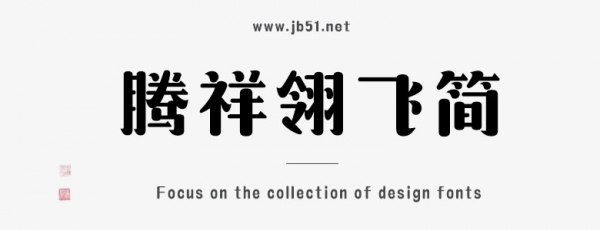
騰祥翎飛簡(jiǎn)是一款不錯(cuò)的藝術(shù)字體,由騰祥字庫出品,既保持字形規(guī)范、布白合理,保證版面效果整齊,又不失字形本身的俏麗與意趣,風(fēng)格獨(dú)特、別致,適合應(yīng)用于藝術(shù)設(shè)計(jì)、平面宣傳設(shè)計(jì)、網(wǎng)頁設(shè)計(jì),書法字帖等領(lǐng)域,需要的朋友可以前來本站下載。
此款字風(fēng)格為美術(shù)字體。
創(chuàng)作靈感:翎飛體骨架基于圓體風(fēng)格,橫筆融入宋體裝飾,撇、捺采隸書之筆意,點(diǎn)形圓潤(rùn)飽滿,整款字巧妙融合多種特征,既保持字形規(guī)范、布白合理,保證版面效果整齊,又不失字形本身的俏麗與意趣,風(fēng)格獨(dú)特、別致。
本作品可適用于數(shù)字媒體、印刷出版、包裝設(shè)計(jì)、兒童讀物、廣告設(shè)計(jì)、網(wǎng)頁設(shè)計(jì)等。